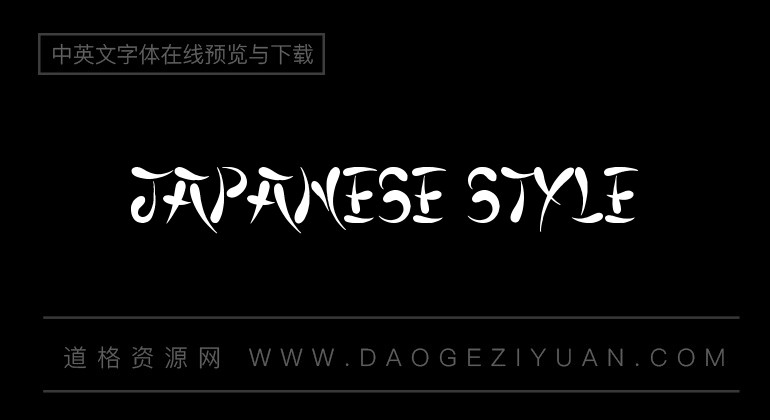
Japanese Style 字体是一种日本传统的字体,它以横线为主要特征,以简洁、精致、优雅的风格著称。它的字符特征是细长的横线,细长的竖线,以及复杂的笔画,使其具有独特的日式风格。Japanese Style 字体最常见的应用是用于日本的文字和图形,如日本报纸、书籍、海报等,也可以用于英文文本的排版。内容介绍
Japanese Style是一款非常不错的手写艺术字体,具有很好的视觉感,适合于文化类的宣传设计、商业类品牌的广告和产品包装设计以及个性化文字排版等较多场景。